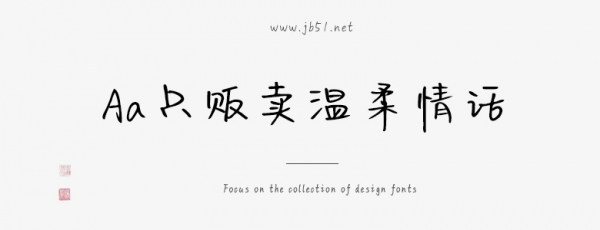
Aa只販賣溫柔情話是一款不錯(cuò)的藝術(shù)字體,由Aa字庫(kù)出品,字體筆觸略細(xì),書(shū)寫流暢 ,具有很好的視覺(jué)感,適合應(yīng)用于藝術(shù)設(shè)計(jì)、平面宣傳設(shè)計(jì)、網(wǎng)頁(yè)設(shè)計(jì),書(shū)法字帖等領(lǐng)域,需要的朋友可以前來(lái)本站下載。